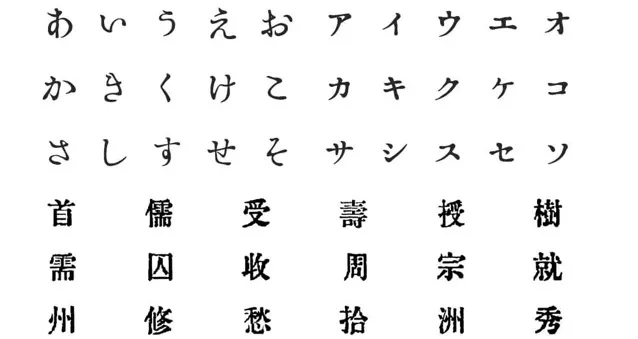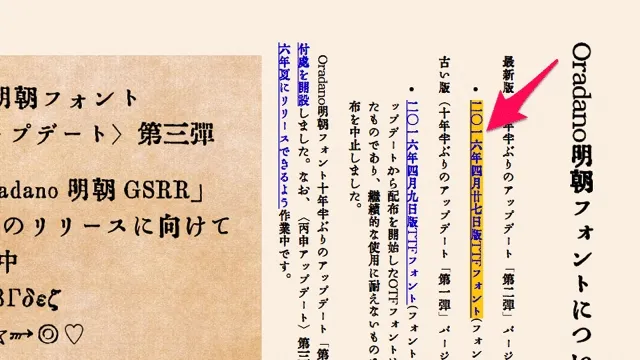
「ORADANO Mincho 明朝」一款日本鉛字印刷效果字體,可免費商用,很有味道的一款印刷字體,非常適合用來做平面設計。 2003年第一版後開始持續更新,很有味道的一款印刷字體非常適合用來做平面設計。數十年後今年6月推出第二版,收錄非常多的漢字字型,後又追加青空文庫使用頻率最高的前兩千個漢字外,亦收錄 1981 年版最常使用漢字字種。